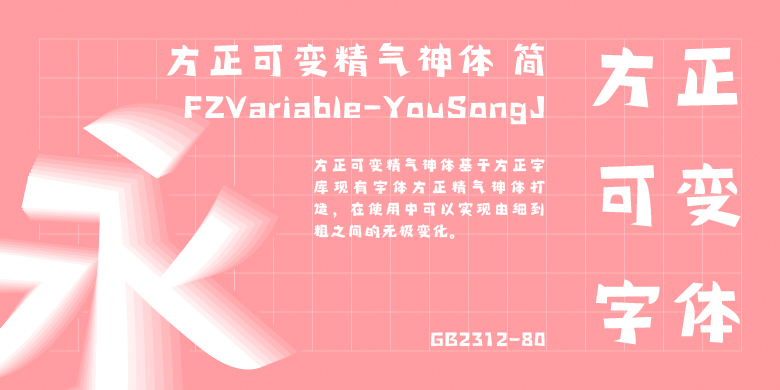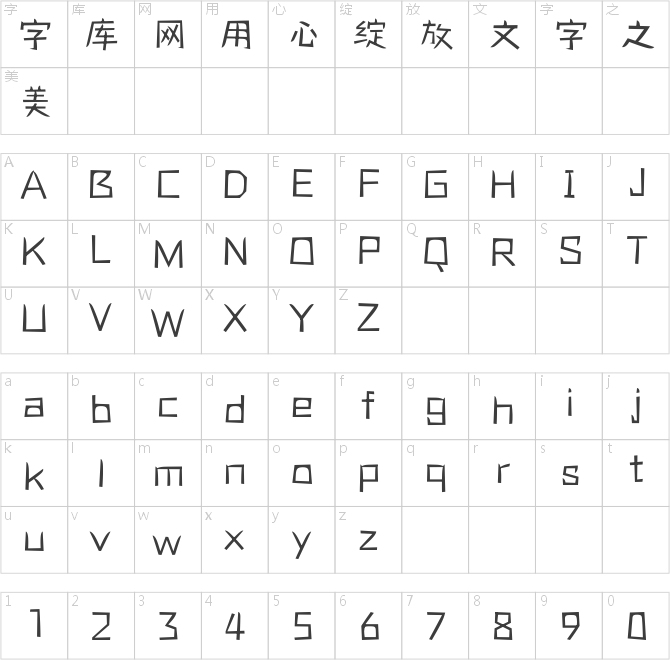
方正可變精氣神體支持文字粗細無級調(diào)節(jié),設(shè)計師通過調(diào)整字重軸(Weight)的變化,可以實現(xiàn)字形的平滑連續(xù)的細微調(diào)整,滿足不同版式的設(shè)計需求。 方正精氣神體家族字體設(shè)計靈感來源于傳統(tǒng)年畫中所帶有的“精氣神”韻味,傳統(tǒng)而又帶有靈氣的感覺。這款字體筆畫較粗,首先帶給人一種敦厚質(zhì)樸的感覺;鉛筆產(chǎn)生的自然肌理又使字體頗具有手寫意味;在負形空間的處理上,統(tǒng)一形成了較小的負形空間,使字體字體看起來穩(wěn)重端正而又不呆板,更加具有趣味性。